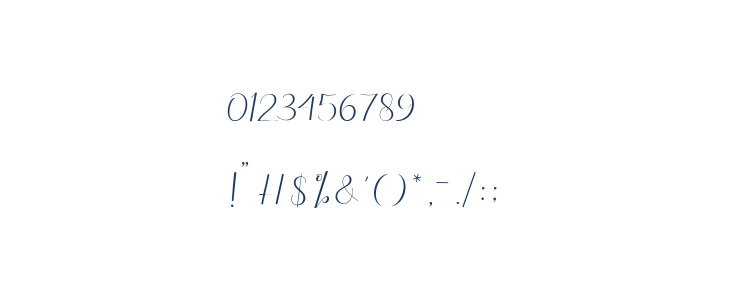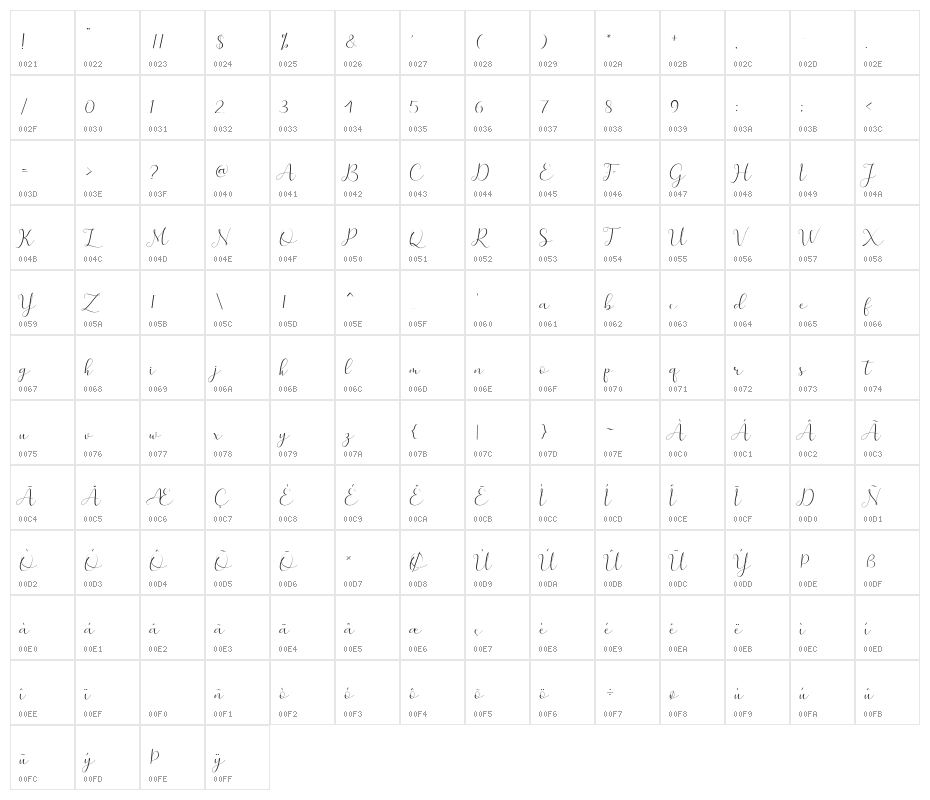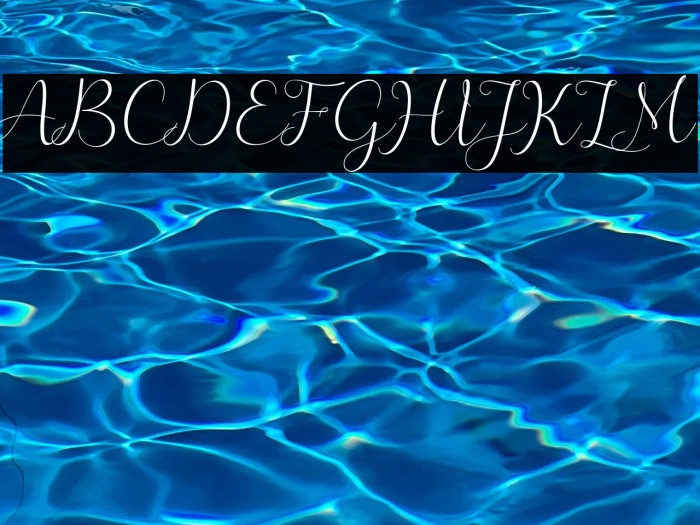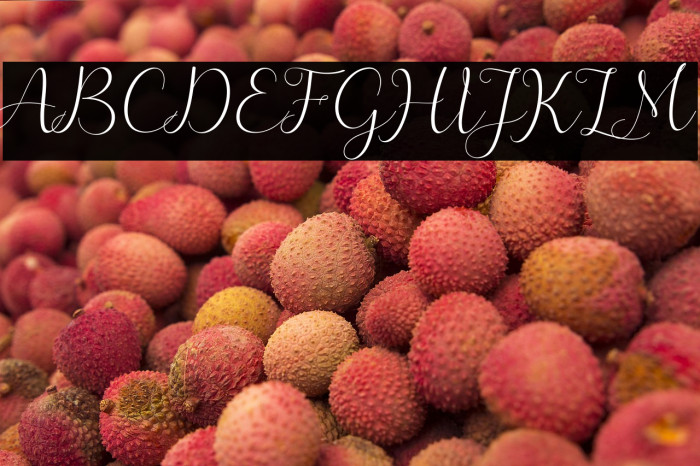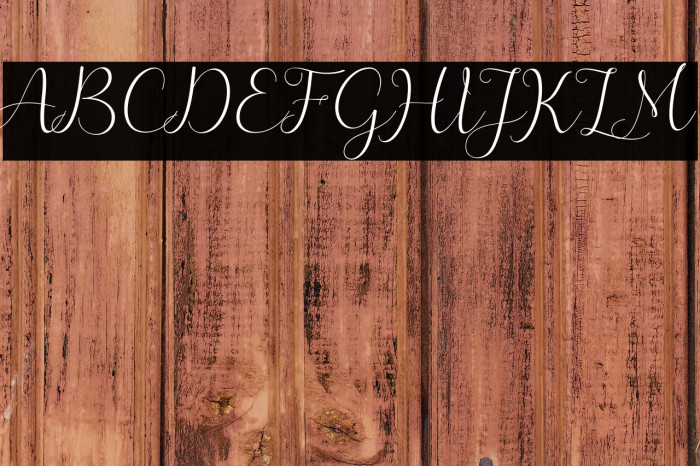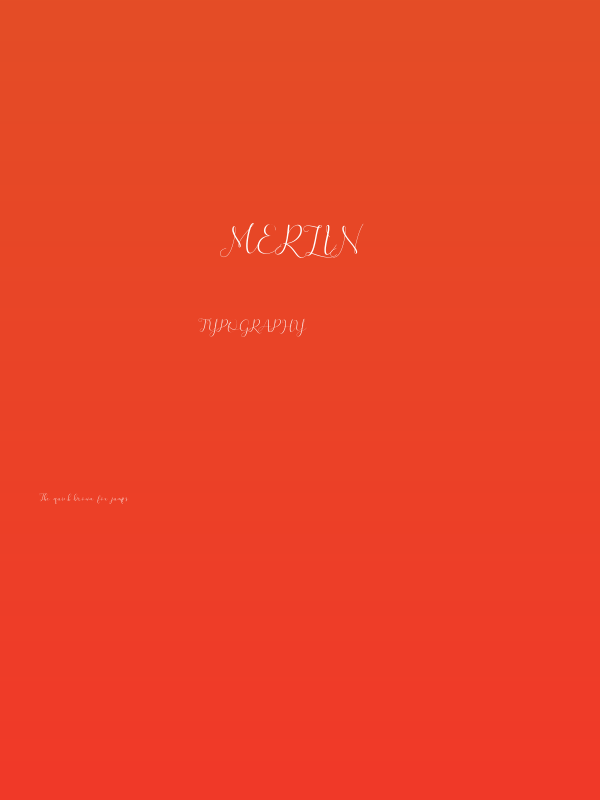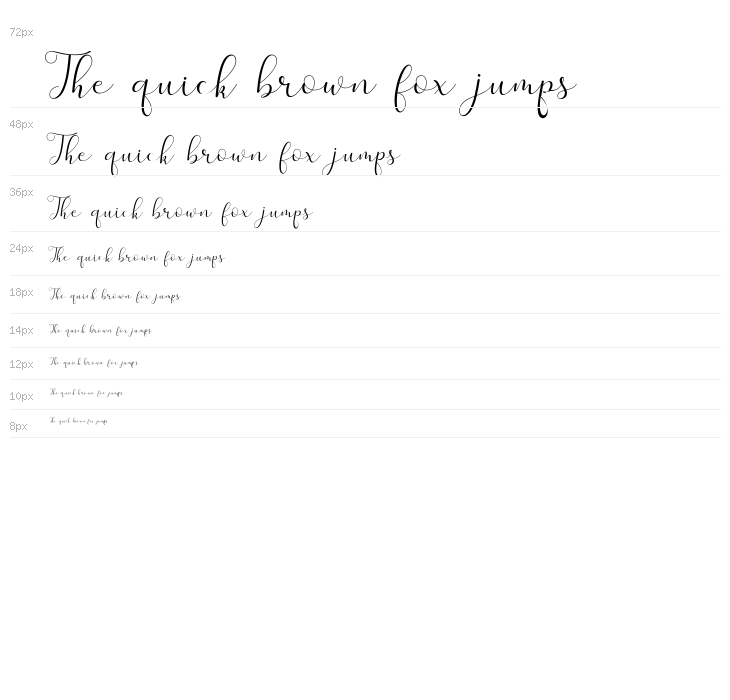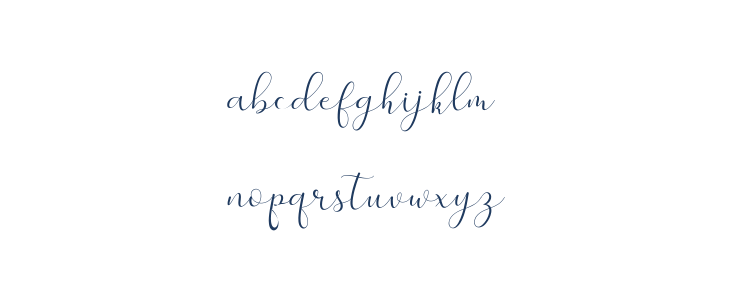
merlin Font
✎ Script
| Gesamtstil | Elegant |
| Anwendungsfall | Logos, Invitations, Branding |
| Vorgeschlagene Projekte | Ideal for wedding invitations, elegant branding, luxury product packaging, and high-end stationery. |